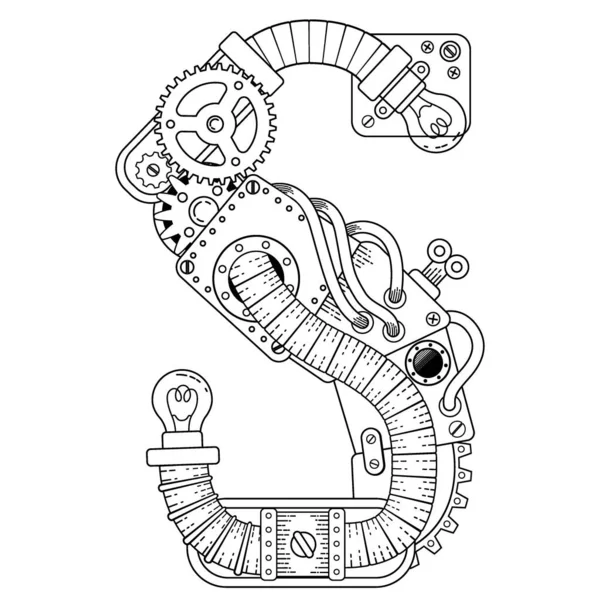
27 лучших шрифтов в стиле стимпанк для ретрофутуристического дизайна
Шрифты в стиле стимпанк относятся к отдельной категории. Эти творческие, завораживающие, ретрофутуристические шрифты сочетают старое с новым, вызывая в воображении образы Англии викторианской эпохи и американского Дикого Запада.
Они создают уникальную эстетику, которая идеально подходит для некоторых типов обложек научно-фантастических и фэнтезийных книг, постеров фильмов и модных дизайнов.
Ниже мы перечислили 27 лучших шрифтов в стиле стимпанк (бесплатных и платных), которые нам удалось найти. Эти шрифты обязательно привлекут ваше внимание шестерни жужжание.
Что такое стимпанк-шрифты?
Стимпанк — поджанр научной фантастики, вдохновленный модой 19-го века и паровой техникой. Он сочетает в себе старомодную эстетику с элементами научной фантастики. Подумайте о летающих очках, шестернях, угле, нижних юбках, цилиндрах и часах.
Стимпанк превратился в субкультуру, вдохновившую многих романов, игр и фильмов.
Действие этих творческих работ обычно происходит в антиутопическом мире, в котором технический прогресс основывался на паровой машине.
Шрифты в стиле стимпанк — это шрифты, которые пытаются отразить эту уникальную эстетику и субкультуру. Жестких правил о том, как должны выглядеть шрифты в стиле стимпанк, не существует, но обычно они характеризуются такими особенностями, как:
- Дизайн в викторианском стиле
- Механические элементы (зубцы, шестерни, трубы и т. д.)
- Необычные или сильно декорированные буквы
27 лучших шрифтов в стиле стимпанк
1. Цветной 3D-шрифт в стиле стимпанк — Наш лучший выбор Во-первых, у нас есть этот невероятно детализированный цветной 3D-шрифт в стиле стимпанк от Cruzine.
Цветные шрифты, подобные этому, используют относительно новый тип формата шрифта, называемый OpenType SVG. Этот формат позволяет дизайнерам включать в шрифты более богатые детали, такие как цвета, градиенты и текстуры.
Вот почему этот шрифт может выглядеть так реалистично и имеет такой классный 3D-эффект. Недостатком является то, что вам понадобится современное программное обеспечение для дизайна (например, illustrator 2018+ и Photoshop 2017+), чтобы правильно открыть этот шрифт.
Почему это наш лучший выбор? 3D-эффект гиперреалистичен и заставляет ваш текст выглядеть так, как будто он сделан из болтов, гаек и металла. Больше стимпанка не бывает.
2. Starship Далее у нас есть еще один фантастический шрифт в стиле стимпанк от Cruzine. Starship украшен орнаментальными винтажными буквами с замысловатыми завитками и диковинными завитушками.
В нем есть нотки элегантности и индивидуальности. Разве вы не можете представить, что он напечатан на боку таинственного парового летательного аппарата в какой-то вымышленной стране?
3. OctopusВот еще один уникальный ретро-шрифт с ярко выраженной эстетикой в стиле стимпанк. Он поставляется в шести стилях: обычный, гранж, встроенный, встроенный гранж, полужирный и полужирный гранж. Встроенный гранж — наш личный фаворит. Текстура и сложная детализация делают буквы действительно уникальными. Octopus также является хорошо читаемым шрифтом, поэтому он хорошо подходит для заголовков и заголовков.
4. Steampunk Далее у нас есть шрифт Steampunk с метким названием от Fractal87.
Это аккуратный машинный шрифт с множеством сложных деталей. Он поставляется в 5 различных стилях: 3 черных стиля и 2 цветных. Раскрашенные версии — наши фавориты, они имеют заводной узор из взаимосвязанных шестеренок белого и медного цвета.
5. Викторианская коллекцияДалее у нас есть огромная коллекция викторианских шрифтов, которая заставит вас подумать, что вы отправились в прошлое, в 19 век. Всего в этом гигантском пакете 1814 глифов.
Существует две основные версии шрифта: King Edward и Queen Elizabeth. Оба этих шрифта в викторианском стиле очень декоративны и орнаментальны, поэтому они хорошо подходят для классических дизайнов.
Каждый также доступен в различных стилях, включая обычный, встроенный, контурный, теневой и текстурированный. Вы можете наложить несколько стилей вместе, чтобы получить крутую многоуровневую комбинацию, которая, кажется, спрыгивает со страницы.
В дополнение ко всем обычным глифам вы также получаете доступ к огромной коллекции альтернатив и дингбатов, которые вы можете использовать, чтобы оживить свои проекты.
Часто задаваемые вопросы
Что такое стиль стимпанк?
На стиль стимпанк повлияла викторианская эпоха и европейская промышленная революция 1800-х годов. Вы можете найти его в литературе, музыке, кинематографе, моде и графическом дизайне. В графическом дизайне это шрифты и иллюстрации в винтажном стиле, часто с креативными механизмами или вдохновленные элегантным дизайном английских этикеток.
Какой лучший шрифт для стимпанка?
Лучшие шрифты в стиле стимпанк имеют обычные и грубые начертания от английских и шотландских лейблов.